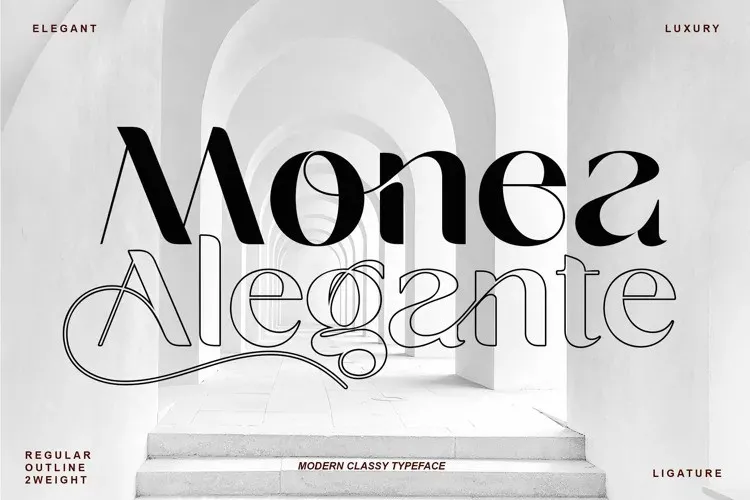
A Monea Alegante Font é uma nova adição à família das fuentes sans serif, criada pelo designer independente Sansakerta. Com seu estilo vintage moderno e sofisticado, essa fonte traz um ar de nostalgia fresco e uma dose apropriada de leveza e originalidade. Ela se destaca tanto no formato de texto como nas aplicações visuais que exigem maior atenção visual, oferecendo uma leitura clara em qualquer tamanho. Ideal para criação de marcas, design de logotipos, marca de roupas, embalagens de produtos e cabeçalhos de revistas ou simplesmente uma base interessante para textos sobre qualquer imagem de fundo. Com um design único e versátil, a Monea Alegante Font se destaca como uma opção elegante para estilos que valorizam tanto o clássico quanto o moderno. Suas linhas curvas suaves e detalhes refinados dão ao texto uma aparência vibrante, enquanto seu tamanho variável permite um uso versátil em diferentes ambientes de design. A Monea Alegante Font é a escolha ideal para quem busca uma fonte que traz o bom gosto do passado à sua identidade visual atual.